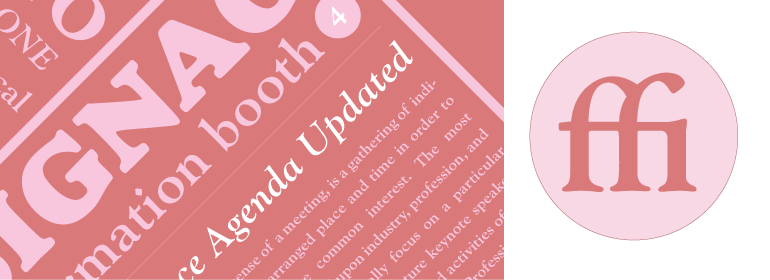
Monotype Goudy™
Over the course of 50 years, the charismatic and enterprising Frederic W. Goudy designed more than 100 typefaces; he was the American master of type design in the first half of the twentieth century. Goudy Old Style, designed for American Type Founders in 1915-1916, is the best known of his designs, and forms the basis for a large family of variants. Goudy said he was initially inspired by the cap lettering on a Renaissance painting, but most of the flavor of this design reflects Goudy's own individualistic style. Recognizable Goudy-isms include the upward pointing ear of the g, the diamond-shaped dots over the i and j, and the roundish upward swelling of the horizontal strokes at the base of the E and L. The italic was completed by Goudy in 1918, and is notable for its minimal slope. Goudy Bold (1916-1919) and Goudy Extra Bold (1927) were drawn not by Goudy, but by Morris Fuller Benton, who was ATF's skillful in-house designer. Goudy Catalogue was drawn by Benton in 1919-1921 and was meant to be a medium weight of Goudy Old Style. Goudy Heavyface was designed by Goudy for Monotype in 1925, and was intended to be a rival to the successful Cooper Black. Goudy Modern was designed by Goudy in 1918; its small x-height, tall ascenders and shorter caps impart a spacious and elegant feeling. Benton designed Goudy Handtooled, the shaded version that has just a hairline of white through its bold strokes. The Goudy faces, especially the bolder weights, have long been popular for display and advertising design. They continue to pop up all over the world, and still look reassuring to our modern eyes."